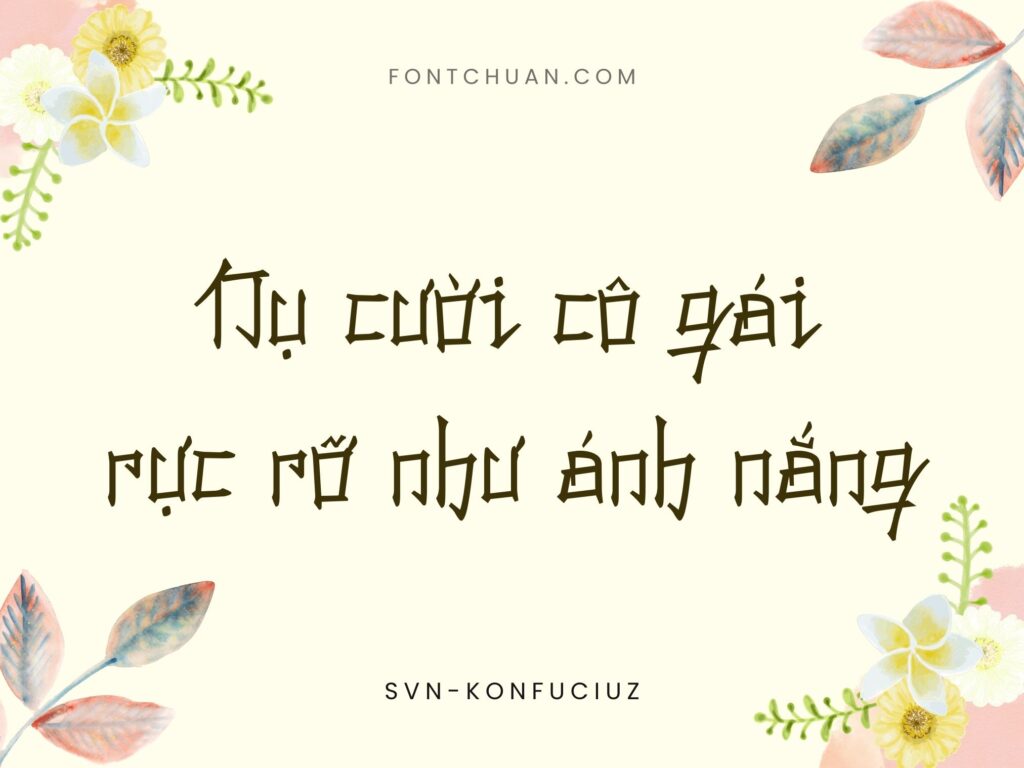
Font SVN Konfuciuz Việt Hóa
Tác giả Font: Apostrophic Labs
Font SVN Konfuciuz là phiên bản Việt hóa của kiểu chữ Konfuciuz, được thực hiện bởi STYLEno.1 Fonts. Konfuciuz là một kiểu chữ hiển thị lấy cảm hứng từ phong cách Á Đông, với sự kết hợp giữa các yếu tố hiện đại và truyền thống, tạo nên vẻ đẹp độc đáo và nghệ thuật. Font này bao gồm các ký tự chữ hoa, chữ số và dấu câu, hỗ trợ đa ngôn ngữ. Với thiết kế đặc trưng, Konfuciuz phù hợp cho nhiều mục đích sử dụng như thiết kế tiêu đề, logo, bao bì sản phẩm và các ấn phẩm truyền thông.
SVN Konfuciuz lý tưởng cho các dự án thiết kế yêu cầu sự độc đáo và nghệ thuật, đồng thời có thể ứng dụng linh hoạt như một Font chữ ẩm thực, giúp các thương hiệu nhà hàng, quán ăn hay thực phẩm thể hiện phong cách gần gũi, hấp dẫn và nổi bật. Ngoài ra, font này cũng thích hợp làm Font chữ spa, mang đến vẻ thanh lịch, tinh tế và thư giãn cho các thương hiệu chăm sóc sức khỏe, làm đẹp hay spa. Nhờ sự đa dụng, SVN Konfuciuz vẫn phù hợp cho các ngành quảng cáo, giáo dục, công nghệ, và các sự kiện đặc biệt như Tết, Giáng sinh, Halloween và các lễ hội khác.